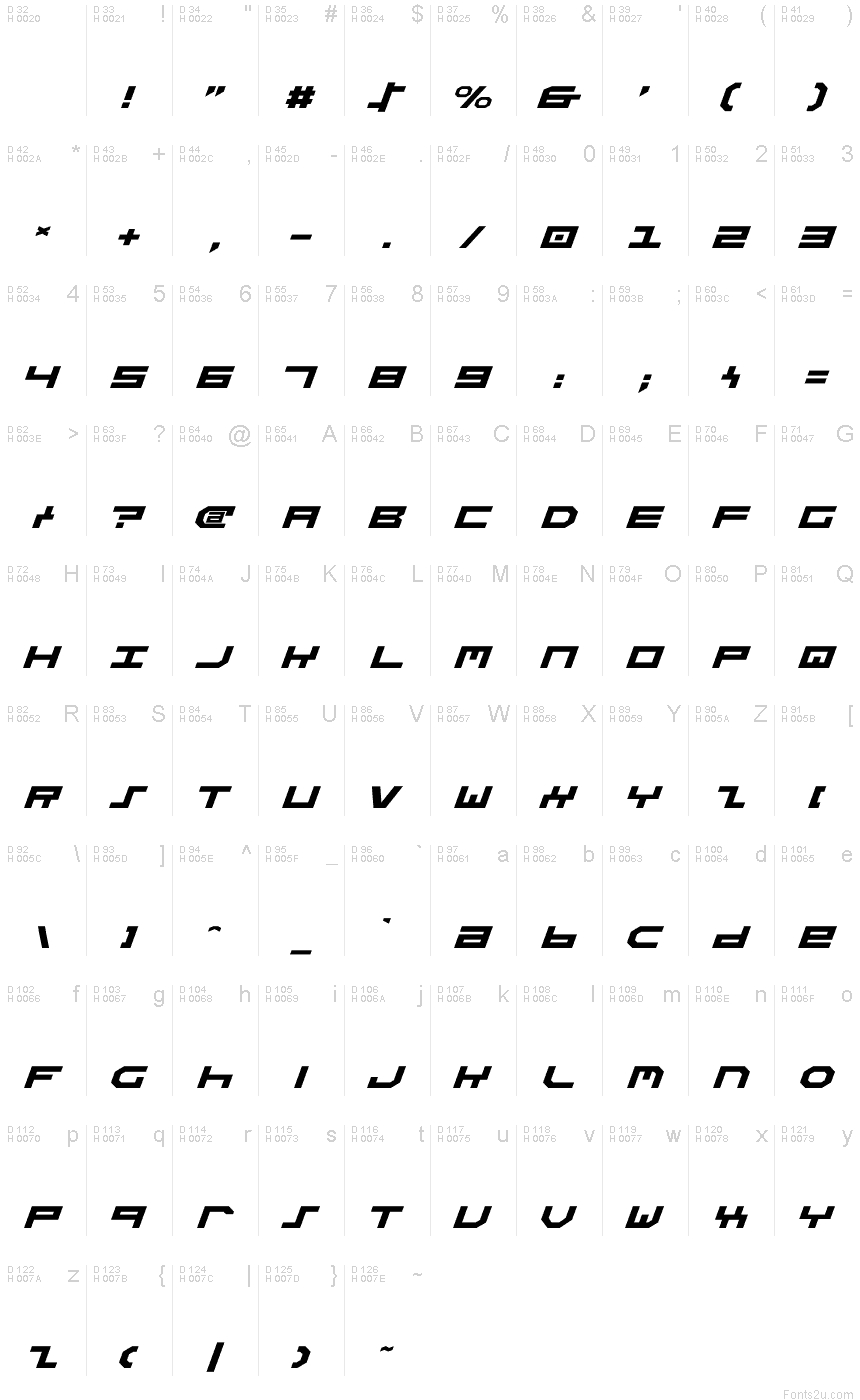
Stuntman Expanded Italic od Iconian Font je bezplatné techno display písmo s rychlou, šikmou siluetou a širokými, hranatými znaky. Jeho vzhled tvoří robustní geometrické tvary, ostré diagonální řezy a useknuté rohy, díky kterým působí jako grafika z akčního sci-fi filmu.
Přirozeně sedí na plakátech, herních logách, sportovním brandingu, titulcích, obalech alb i krátkých nadpisech na obalech, kde je potřeba rychlost spíše než jemnost. Široký postoj dodává i krátkým slovům filmový nádech, takže nejlépe vynikne, když necháte písmena volně dýchat, místo abyste je tísnili v hustém textu.
Stuntman Expanded Italic
Dan Zadorozny